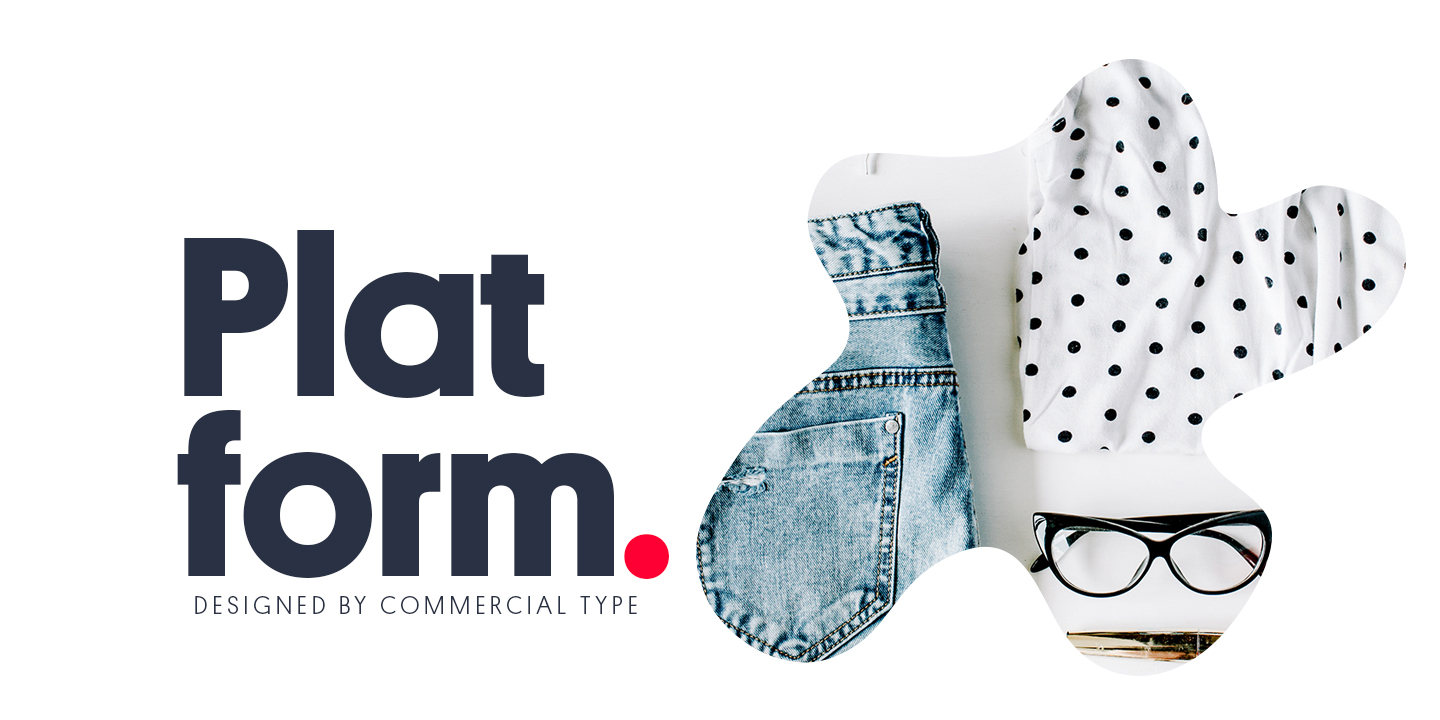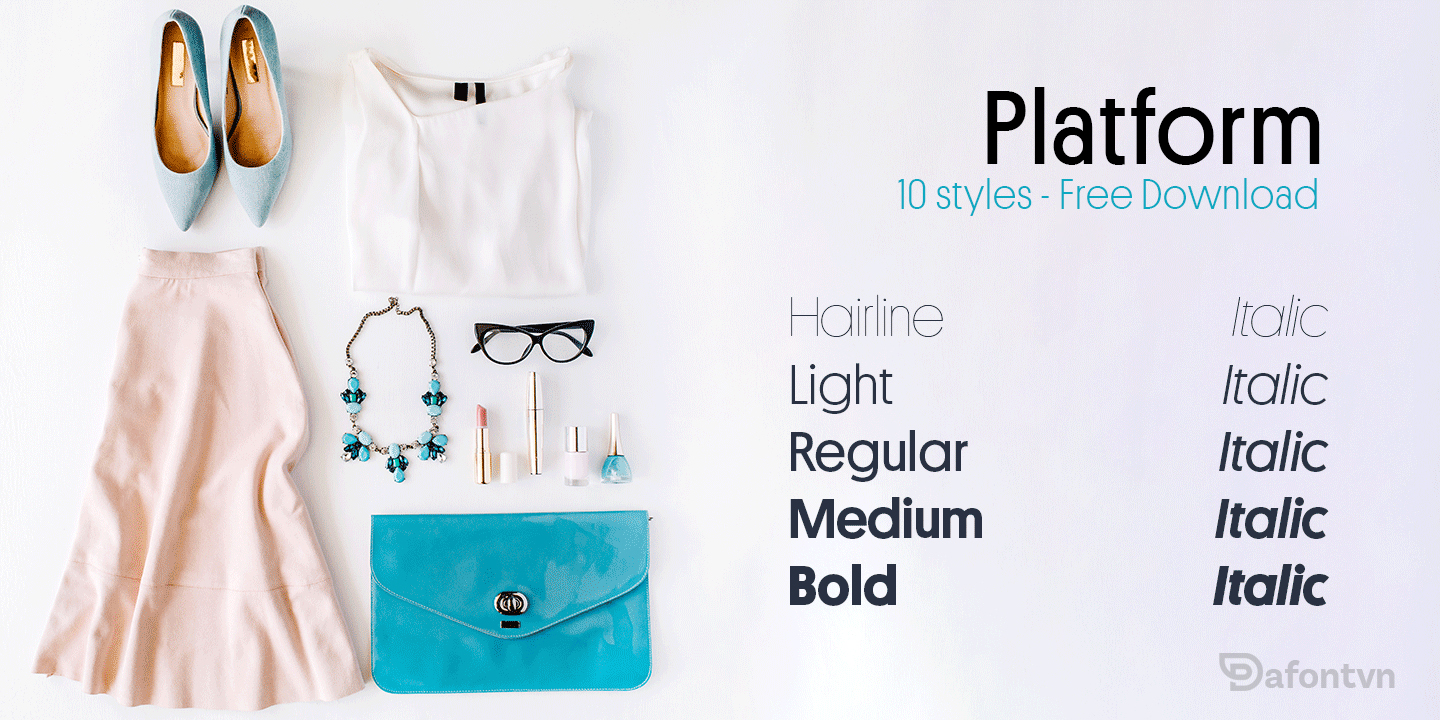
Platform là thiết kế của Berton Hasebe. Căn bản, family này là sự đột phá của dòng geometric sans serif, một trong những loại type được sử dụng phổ biến nhất trong các thiết kế của thế kỉ 20, đã có thể áp dụng vào thiết kế hiện đại như thế nào. Không nhằm mục đích hoàn hảo, Platform thay vào đó lại là một thiết kế tài tình của sự vụng về vốn có trong các chữ cái, rút ra những gì tinh túy nhất của thiết kế hiện đại đưa vào trong con chữ.